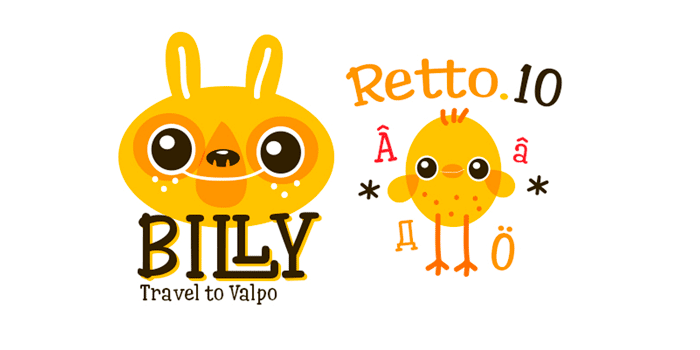
[Cartoon] Cucho Việt hóa
Thông tin về font Cucho
Lại một typeface nữa đến từ RodrigoTypo. Không có gì nhiều để nói, preview nói lên tất cả. Đặc biệt typeface này có rất nhiều kí tự ligature cho các bạn chọn lựa nhá. Nhớ bật tính năng opentype ligature và thưởng thức! Full bộ 3 font Regular + Bold và Ornament đó nhá.